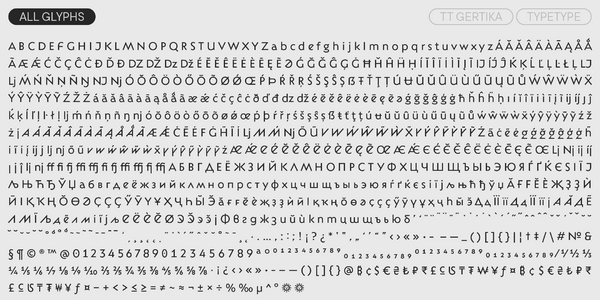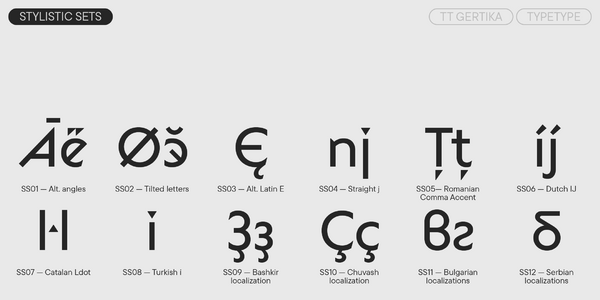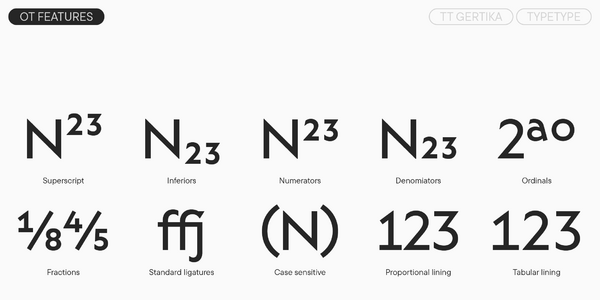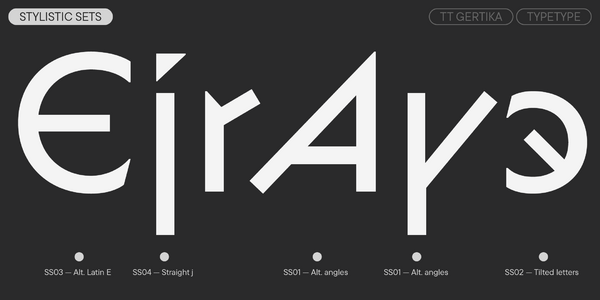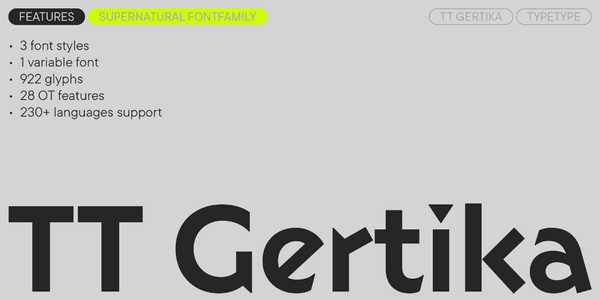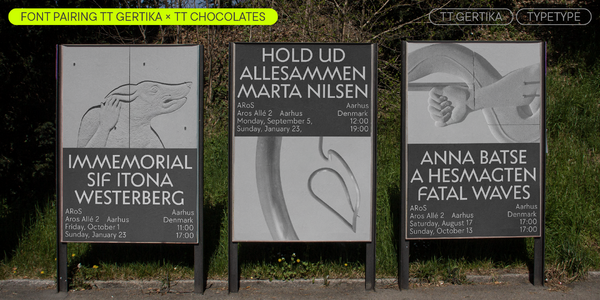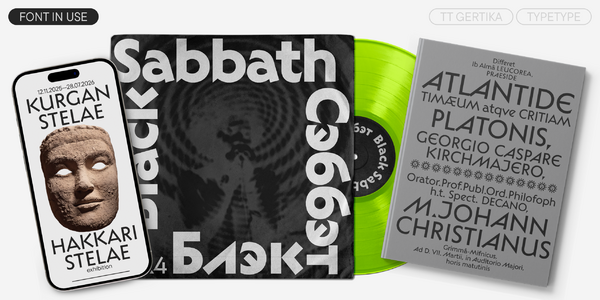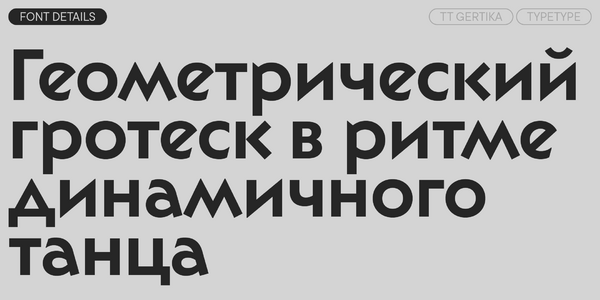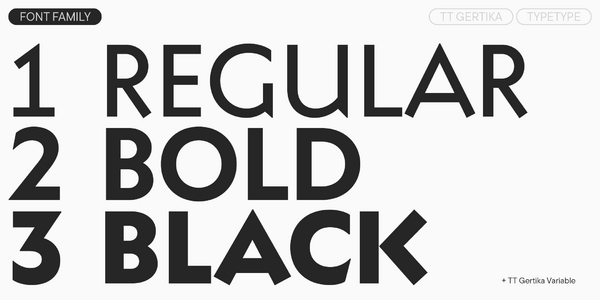
TT Gertika
TT Gertika — ТТ Гертика
Произносится «ТТ Гертика». Слово «Gertika» является неологизмом. Буквы «TT» являются аббревиатурой названия компании.
TT Gertika — геометрический гротеск с динамичным характером и танцующим ритмом. Это акцидентный шрифт, в котором подружились современность и архаичность.
TT Gertika — геометрический гротеск с особой динамикой и танцующим ритмом
TT Gertika совмещает в своей графике элементы современности и некоторой первобытности. Шрифт имеет уникальные характерные особенности: разноширинные пропорции, ассиметричные острые терминалы в знаках типа «S», «С», «З», срезы диагональных штрихов под углом 90°. Также мы разработали разную диакритику для широких и узких форм знаков. При использовании стилистических сетов вы можете изменить настроение и образ шрифта: сделать его более острым и динамичным или, наоборот, округлым и плавным.
Семейство состоит из 4 начертаний: 3 прямых и 1 вариативного
О гарнитуре TT Gertika
Встречайте наш новый акцидентный TT Gertika — шрифт, в котором подружились современность и архаичность!
TT Gertika — геометрический гротеск с динамичным характером и танцующим ритмом. Идея шрифта зародилась из леттеринга на американском плакате второй половины 30-х годов. Мы увидели в буквах множество интересных деталей, которые решили переосмыслить. В результате получился шрифт, отсылающий к чему-то древнему, даже первобытному, но при этом современный.
Отличительные черты TT Gertika — грубые срезы диагональных штрихов под углом 90°, острые «прямолинейные» стыки элементов букв, ассиметричные острые терминалы в знаках типа «S», «С», «З», которые контрастируют с общей геометричностью форм, а также заметная разноширинность в пропорциях. Интересно, что для широких и узких знаков мы разработали разную диакритику.
Настроение и образ шрифта может значительно меняться благодаря стилистическим сетам: вы можете сделать его более строгим и динамичным, либо, наоборот, округлым и плавным. Кроме того, в гарнитуру входит вариативный шрифт, меняющийся по оси жирности. Это позволяет ещё свободнее управлять характером TT Gertika.
Этот шрифт подходит для создания акцентов и лучше всего проявляет себя в крупном размере, при этом хорошо работает и в небольших текстовых вставках. Он будет отлично выглядеть на обложках книг и журналов об истории и искусстве, может украсить пространство выставки и гармонично впишется в айдентику брендов, черпающих вдохновение в фольклоре или произведениях примитивистов.
TT Gertika включает:
• 4 начертания: 3 прямых и 1 вариативный шрифт;
•  922 знака в каждом начертании;
• 4 стилистических сета;
•  28 OpenType фич;
• Поддержку 230+ языков.
ss01 | Alternative angles
A M
ss02 | Tilted letters
ǼÉ
ss03 | Alternative Latin E
ǼÉ
ss04 | Straight j
íj ij
ss10 | Chuvash localization
Ҫ ҫ